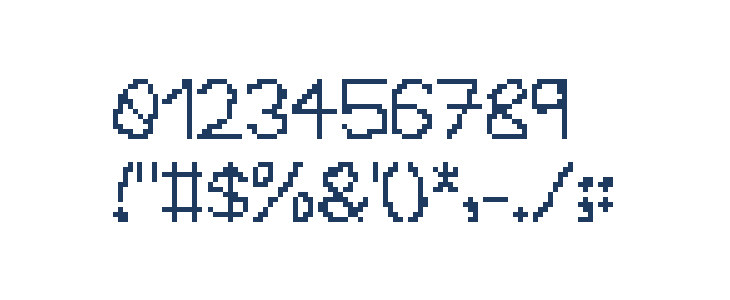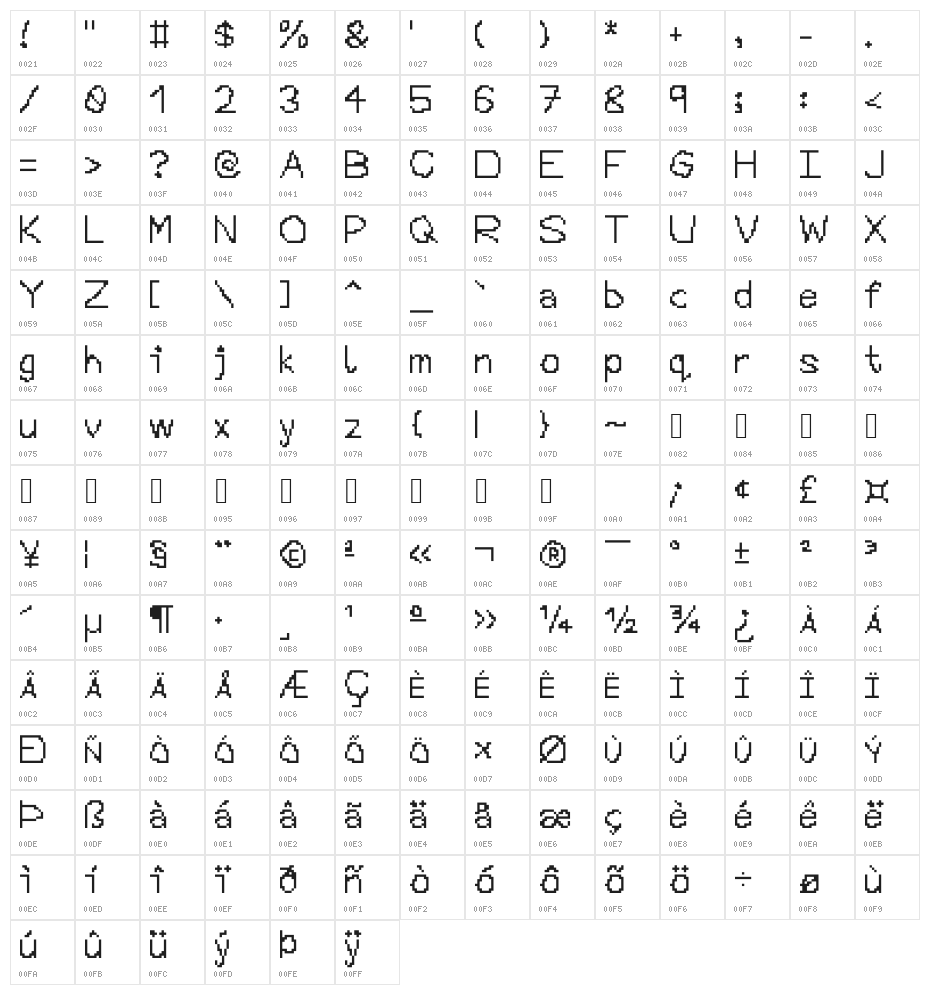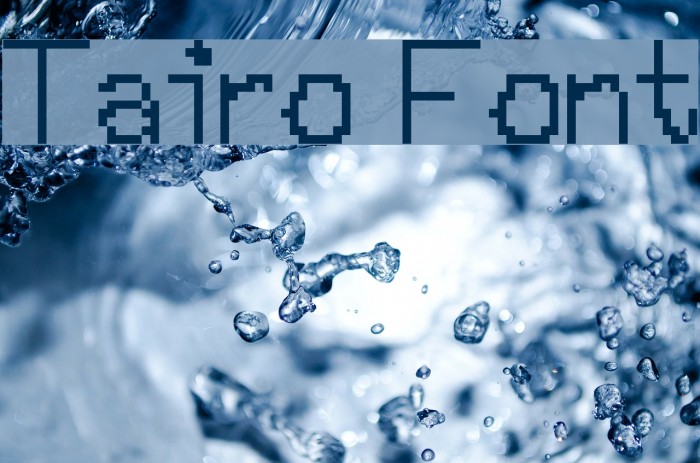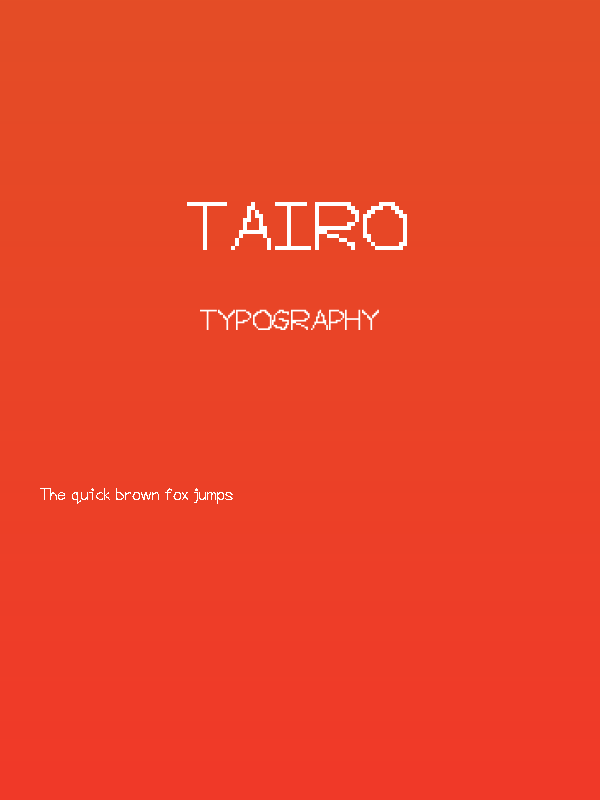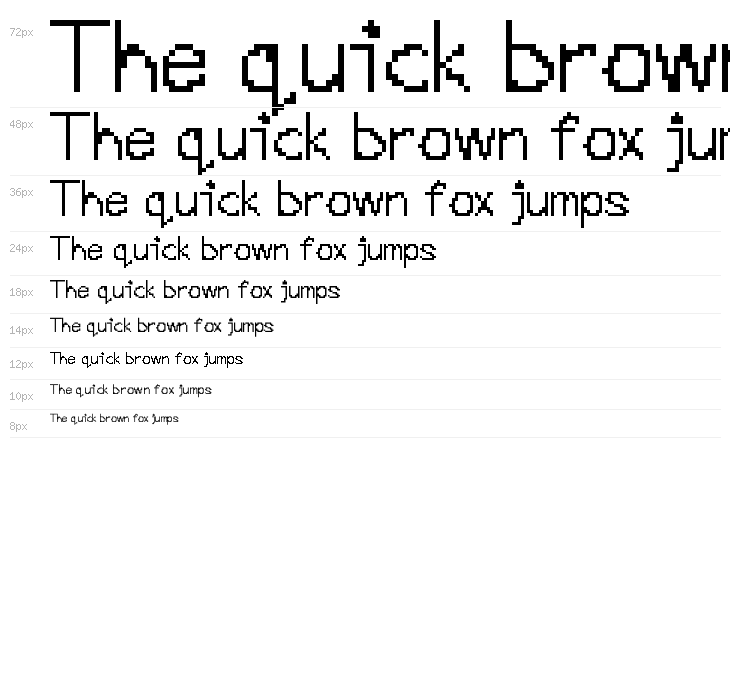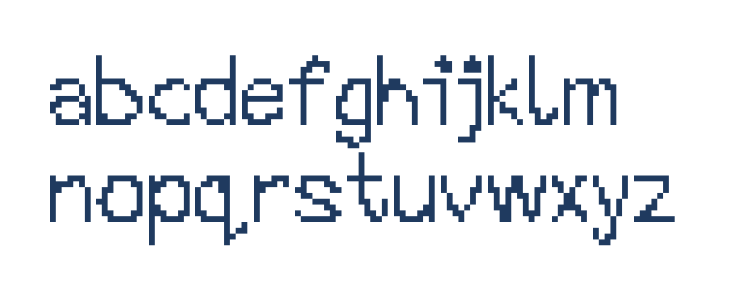
Tairo Font
| Estilo geral | Retro, Digital |
| Caso de uso | Logos, Headlines, Digital Art |
| Projetos propostos | Ideal for video game design, retro-themed posters, digital art projects, and any creative work that requires a nostalgic digital touch. |